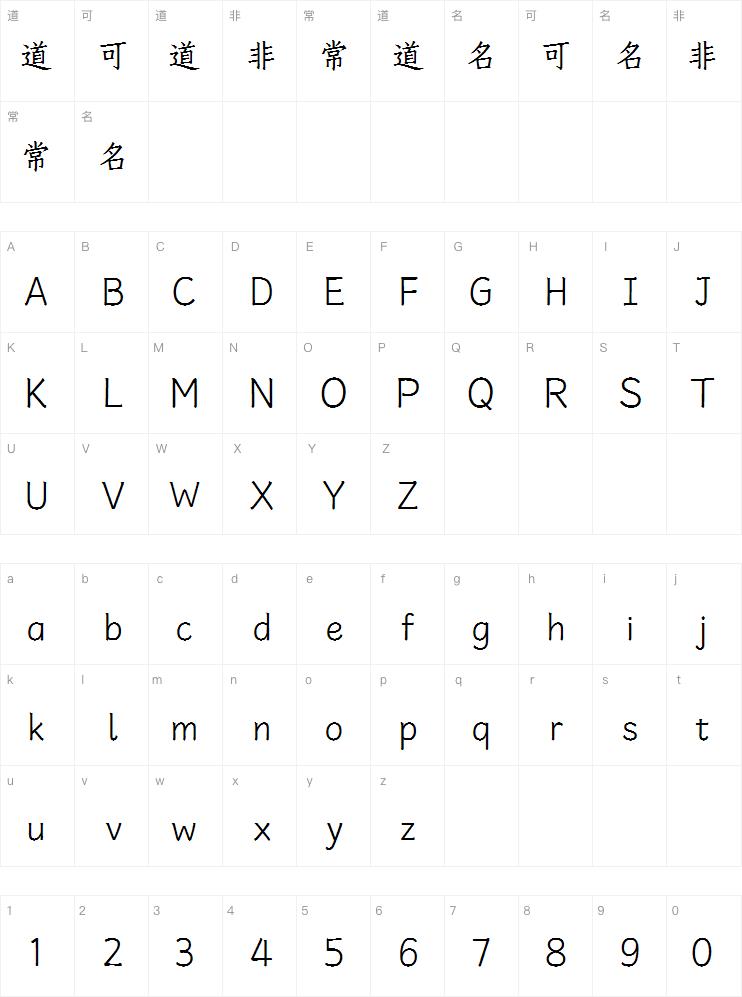
字魂班马楷体 W1
字魂班马楷体 W1字体是一款楷体、创意标题字、正文、刻本字体,该字体包含8488个中文、字母、符号和数字,具有清秀纤细的风格,笔画轻盈灵动、字面雅致,可以满足您设计上的各种需求,该字体主要用于小字号正文阅读、出版排版等场景。具有笔画纤细、字面雅致的温润中国风格,主要用在小字号正文、办公文档、文艺排版等场景上,可以传达出清晰轻盈、雅致克制、温和亲近的感觉。
字魂班马楷体 W1